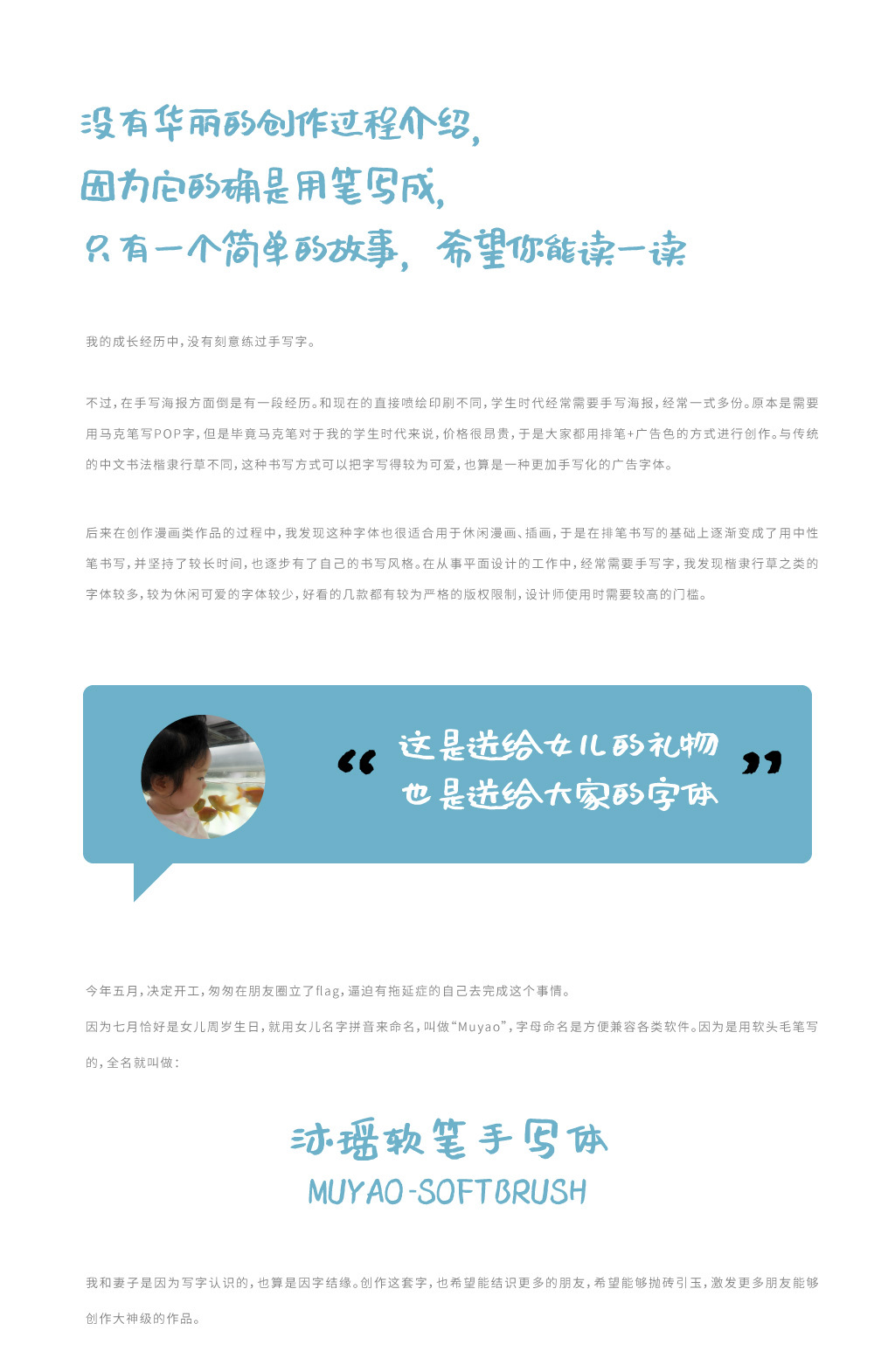
沐瑤軟筆手寫體 詳情頁
字體名稱: 沐瑤軟筆手寫體
作者版權: 春顏秋色
沐瑤軟筆手寫體
沐瑤軟筆手寫體介紹
2020年6月23日更新:修改了“假”字的錯誤筆畫。
沐瑤軟筆手寫體字體Muyao-Softbrush字庫是一款讓人賞心悅目、百看不厭的中文字體,適合各類廣告和產品包裝設計應用,字體大小4.33MB,格式為ttf字體,上傳用戶是Me / ,yD ,作者/版權方為春顏秋色